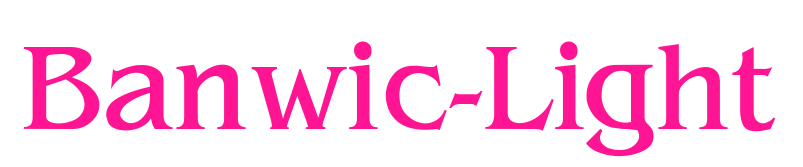
Banwic-Light 详情页
字体名称: Banwic-
Banwic-Light
Banwic-Light介绍
Banwic-Light字体字库是一款让人赏心悦目、百看不厌的英文字体,适合各类广告和产品包装设计应用,字体大小0.04MB,格式为ttf字体,上传用户是afig,作者/版权方为未知